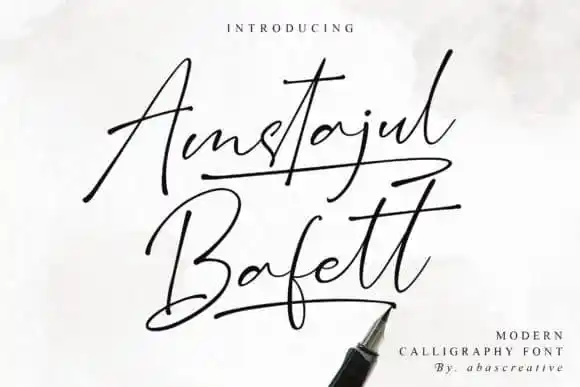
Amstajul Bufett Handwritten Font – Download Grátis
A Amstajul Bufett Handwritten Font foi criada para imitar uma escrita manuscrita natural com grande precisão, oferecendo alternativas para letras minúsculas e sublinhados, além de alternativas de traços curvados e ligaturas. Este tipo de fonte é perfeito para criações que exijam um ar autêntico e delicado, como invitações de casamento, embalagens de produtos, materiais de publicidade ou até mesmo cartões de boas-vindas. O fato de ser PUA codificado significa que você pode facilmente acessar todos os traços e sublinhados desta fonte com grande flexibilidade. Esta fonte é uma escolha perfeita para designers buscando um acabamento elegante e sofisticado em seus projetos, seja ele para o uso em aplicativos de redes sociais ou até mesmo embalagens para produtos.